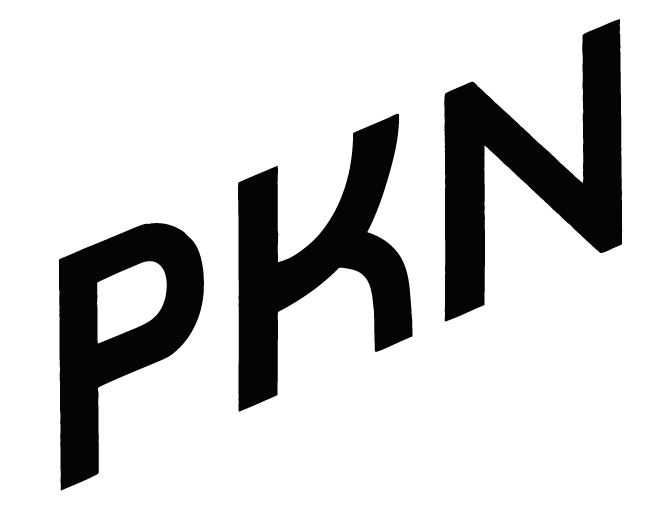
Was für ein Font ist das?
Hallo Typofreunde, ich suche mir die Augen wund, finde aber diesen Font mit dem charakteristischen Versal-K nicht. Vermutlich ist er nachträglich auch noch noch digital schräg gestellt worden. Kann mir jemand helfen?